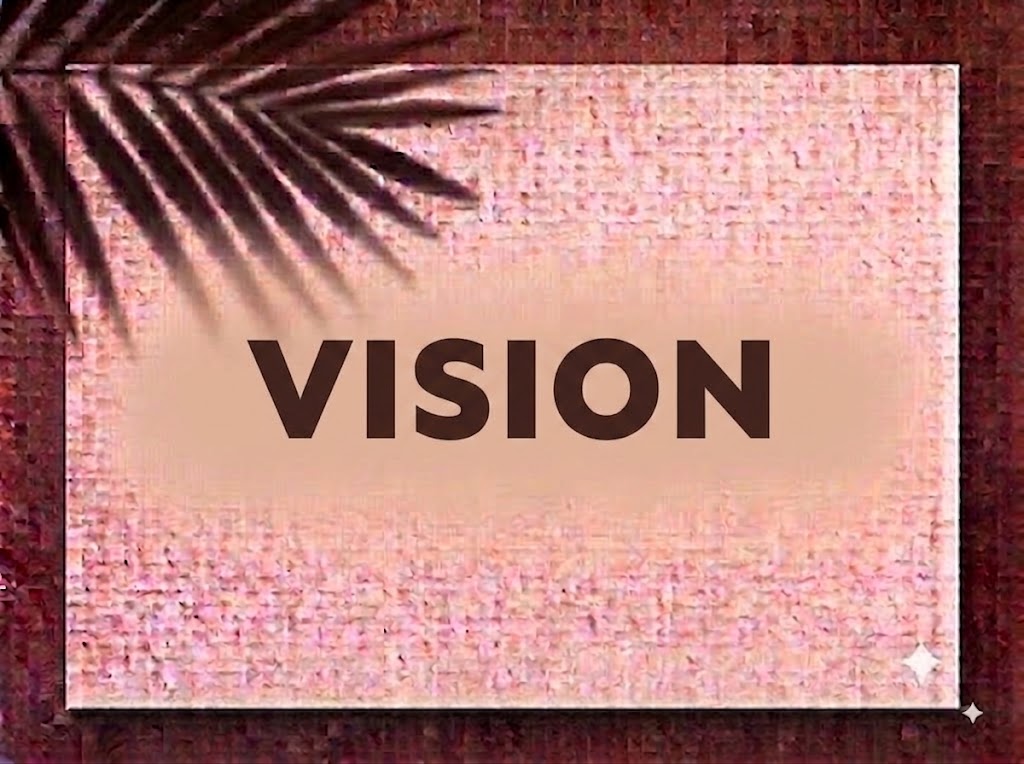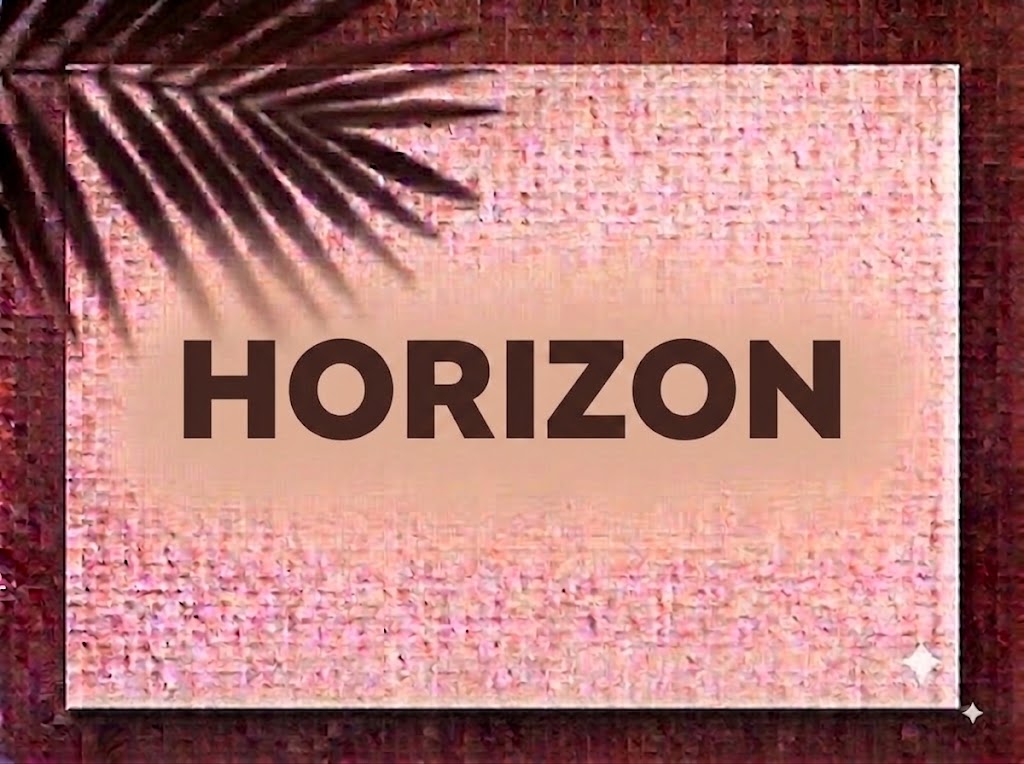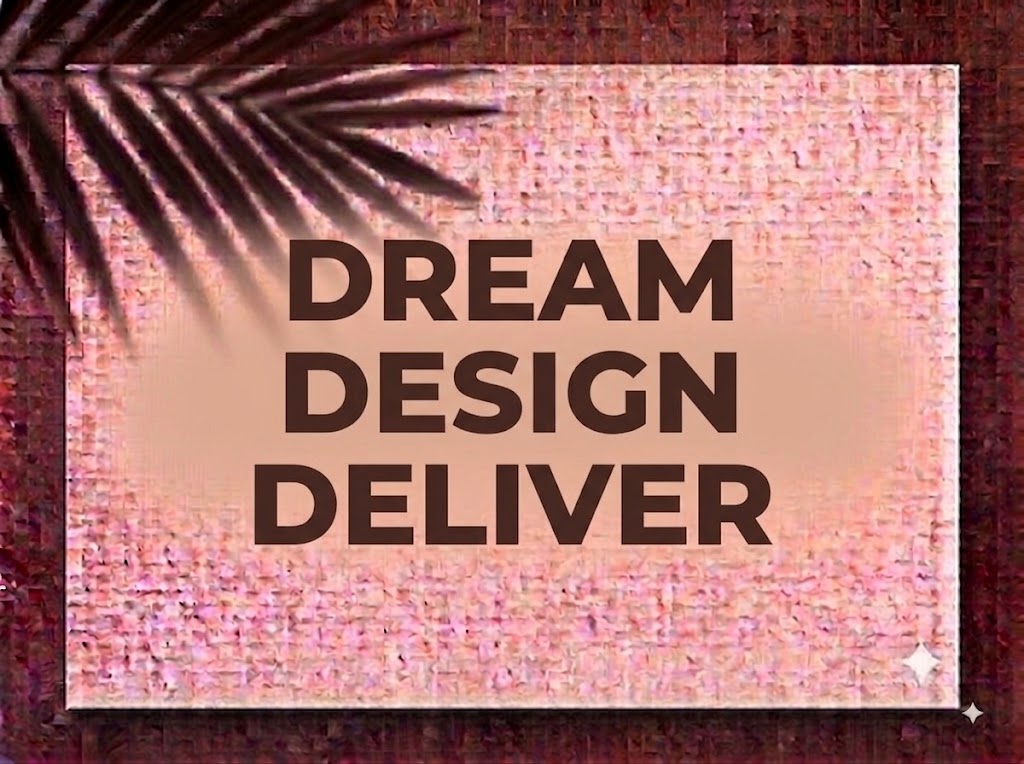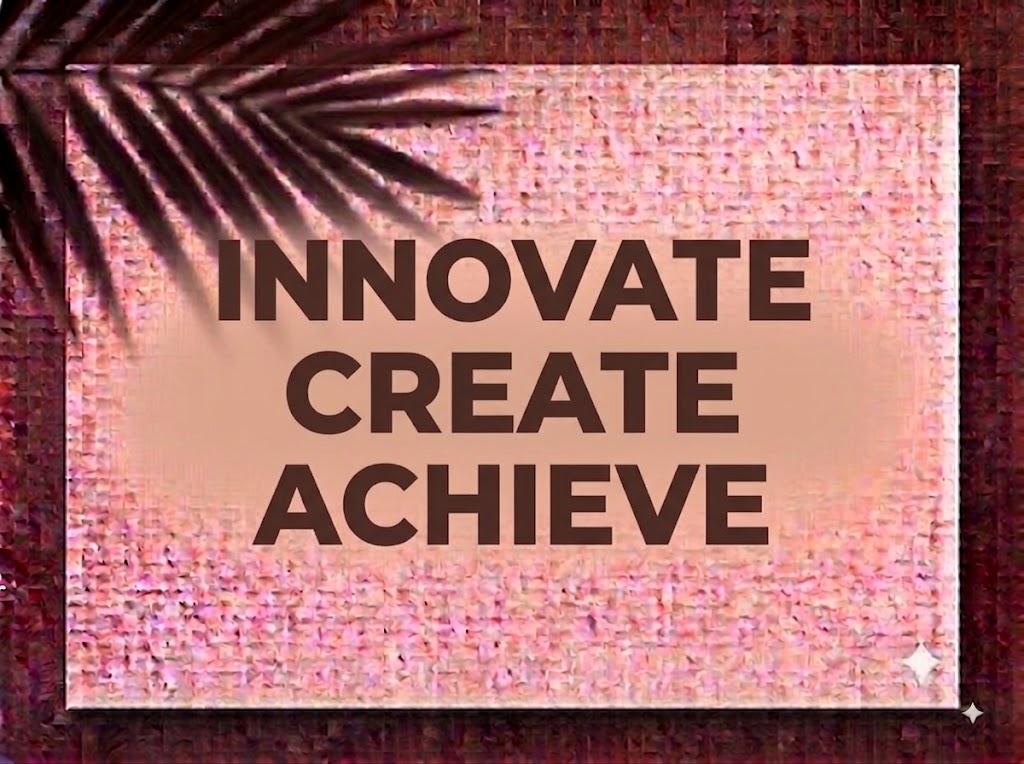
1FTV Sen ExtraBold
Trong thiết kế đồ họa đương đại, các bộ phông chữ không chân hình học (Geometric Sans-Serif) với trọng lượng nét siêu đậm (ExtraBold) luôn giữ vị trí “ông hoàng” về độ nhận diện thị giác và khả năng truyền tải thông điệp nhanh chóng. Cấu trúc chữ rõ ràng, vuông vức kết hợp cùng các đường cong chuẩn xác giúp tiêu đề luôn nổi bật tuyệt đối trên mọi nền tảng số.
Nếu bạn đang tìm kiếm một phông chữ không chân hiện đại, khỏe khoắn, đa năng để làm phụ đề video ngắn, thumbnail YouTube, thiết kế giao diện (UI/UX) hay bộ nhận diện thương hiệu công nghệ, font 1FTV Sen ExtraBold chính là lựa chọn không thể thiếu trong kho tài nguyên của bạn.
Giới thiệu về font 1FTV Sen ExtraBold
Font 1FTV Sen ExtraBold là bộ chữ Sans-Serif thuộc họ font Sen danh tiếng, được phát triển dựa trên cấu trúc hình học tối giản mang hơi thở đương đại:
Tên phông chữ: 1FTV Sen ExtraBold
Đặc điểm nổi bật của phong cách thiết kế Sen ExtraBold
Sức hút của font 1FTV Sen ExtraBold đến từ sự cân bằng hoàn hảo giữa tính thẩm mỹ tối giản và công năng truyền thông mạnh mẽ:
Cấu trúc hình học (Geometric) chuẩn mực: Các đường nét bo tròn ở các chữ cái như
o,c,e,p,b,d,qđược tạo hình từ các khối tròn hoàn hảo, kết hợp cùng các cột nét thẳng tắp mang lại cảm giác thân thiện, trung tính và chuyên nghiệp. -
Độ đậm ExtraBold uy lực: Nét chữ dày dặn, tỷ lệ tương phản thấp giúp từng khối từ trở nên chắc chắn, vững chãi, lập tức thu hút sự chú ý của người xem ngay trong những giây đầu tiên lướt qua.
Khả năng đọc (Legibility) vượt trội: Khoảng mở ký tự (aperture) rộng rãi và chiều cao x-height lớn giúp chữ không bị bết dính nét khi đặt ở kích thước nhỏ hoặc hiển thị trên màn hình điện thoại có độ phân giải thấp.
Khoảng cách giữa các chữ (kerning) và tracking được tối ưu hóa chuẩn xác cho trọng lượng ExtraBold, đảm bảo các khối chữ dài không bị dính vào nhau.
Tích hợp trọn vẹn bộ chữ cái hoa – thường, dãy chữ số 0-9 phom dáng hiện đại cùng hệ thống ký tự đặc biệt, dấu câu thông dụng.
Bản Việt hóa chuẩn chỉnh với hệ thống dấu tiếng Việt được đặt trọng tâm cân đối, tinh gọn, không làm ảnh hưởng đến khoảng cách dòng khi gõ đoạn văn bản.
Hình ảnh demo thực tế của font 1FTV Sen ExtraBold
Khả năng hiển thị của phông chữ này được tối ưu rất tốt trên nhiều tỷ lệ kích thước khác nhau:
Kích thước nhỏ (12pt – 24pt): Cấu trúc nét rõ ràng giúp các câu chữ và dãy số vẫn hiển thị rành mạch, dễ đọc trên giao diện ứng dụng hoặc phụ đề video.
Kích thước lớn (36pt – 72pt): Đây là đất diễn lý tưởng nhất để 1FTV Sen ExtraBold phô diễn toàn bộ sự khỏe khoắn, mạnh mẽ, tạo tác động thị giác bùng nổ cho các dòng tiêu đề chính và bìa thumbnail.
Ứng dụng trong thiết kế đồ họa và làm video
Sở hữu nét cá tính hiện đại và tính ứng dụng linh hoạt cao, font 1FTV Sen ExtraBold mở ra không gian ứng dụng phong phú:
Video ngắn (TikTok, Reels, Shorts, CapCut): Lựa chọn hàng đầu để làm phụ đề tự động (auto-captions), giật tít tiêu đề nổi bật giữa màn hình tỷ lệ 9:16 nhờ độ rõ ràng và bắt mắt tuyệt đối.
Ảnh thu nhỏ YouTube (Thumbnail): Vũ khí tối ưu CTR cho các kênh công nghệ, thể thao, tin tức, tài chính, giáo dục hay vlog đời sống.
Thiết kế Banner, Poster & E-commerce: Hoàn hảo cho các chiến dịch Flash Sale, poster sự kiện thể thao, banner quảng cáo Facebook Ads, Google Ads và sàn thương mại điện tử.
Nhận diện thương hiệu & UI/UX Design: Thích hợp làm logo dạng chữ khối cho các thương hiệu công nghệ, startup, agency truyền thông, ứng dụng di động hoặc tiêu đề website hiện đại.